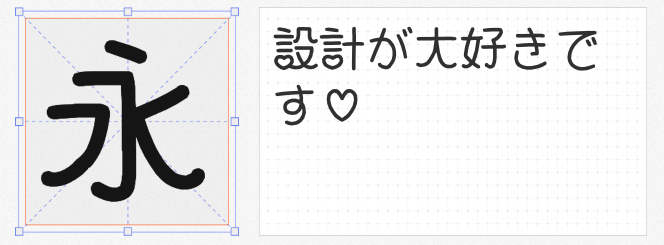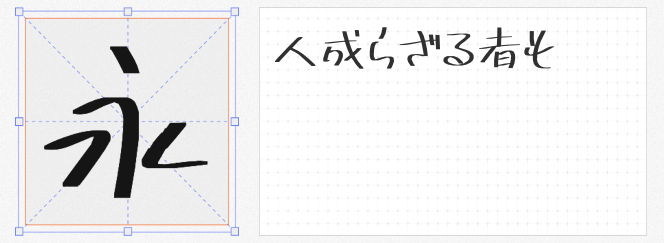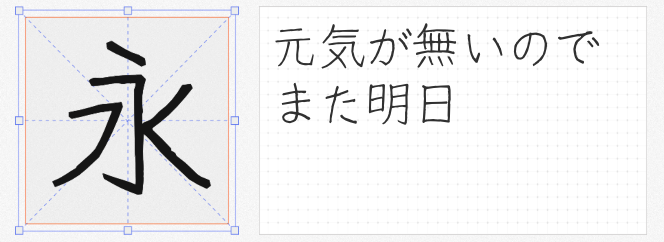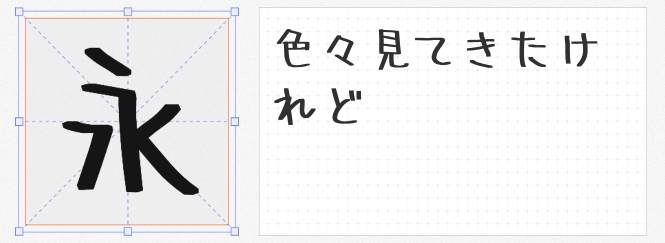
萌动笔尖!四款免费商用日系手写字体,点亮你的可爱设计灵感(*ᴗ͈ˬᴗ͈)ꕤ
在追求个性与温度的设计领域,手写字体总能以独特的笔触传递温暖与生命力。今天,我们精选四款免费商用的日系手写字体,它们以轻盈、随性的笔触,为设计注入治愈系可爱能量,尤其适合追求自然手写感的创作场景。
1. 细鸣字体 B
若需一款轻盈不抢镜的百搭字体,细鸣字体 B 堪称首选。它模拟真实书写痕迹,笔画纤细如发丝,却保有墨水渗透纸背的质感。细鸣字体提供三种字重,无论是清新海报的副标题、文艺书籍的排版,还是产品包装的点缀文字,都能灵活切换氛围。其克制的设计感让小字阅读也清晰舒适,堪称「隐形的设计助手」。
2. 猫猫朋友体
由日文名「にゃしぃフレンズ」直译而来的猫猫朋友体,将「萌」元素融入每个笔画。字体中镶嵌着俏皮的心形图案,仿佛猫咪肉垫踩过纸面留下的印记。圆润的线条与不规则的抖动感,完美复刻手账书写的真实痕迹,适合儿童绘本、甜品菜单、手作品牌等场景。即使纯文字排版,也能透出软萌气息。
3. 无心手写体
这款字体坦诚地展现「不完美」:笔画毛糙、结构松散,却因此充满真实的手写呼吸感。作者摒弃刻意设计,将日常书写的随意性与生命力封存于字库中。推荐用于小尺寸标签、手写便签模拟、复古风海报等场景,其粗粝质感反而能营造「未完成」的艺术张力。
4. 851麻花POP体
日本设计师 8:51:22 pm 打造的这款字体,将手写 POP 广告的热闹感浓缩其中。笔画如麻花般扭曲缠绕,充满动态韵律,尤其适合大促海报、活动标题等需要视觉冲击力的场景。即使纯文字也能形成视觉焦点,搭配荧光色或渐变效果,瞬间点燃版面活力。
这四款字体如同性格迥异的「纸面精灵」——有的轻盈优雅,有的憨态可掬,有的率真洒脱。它们打破了电子屏幕的冰冷感,用墨迹的温度将「手写治愈力」注入设计。更难得的是,全部支持免费商用(使用前请确认最新授权条款),让创意表达再无后顾之忧。下次设计时,不妨让指尖在键盘上「书写」,用这些可爱字体,为作品注入会心一击的温暖吧!